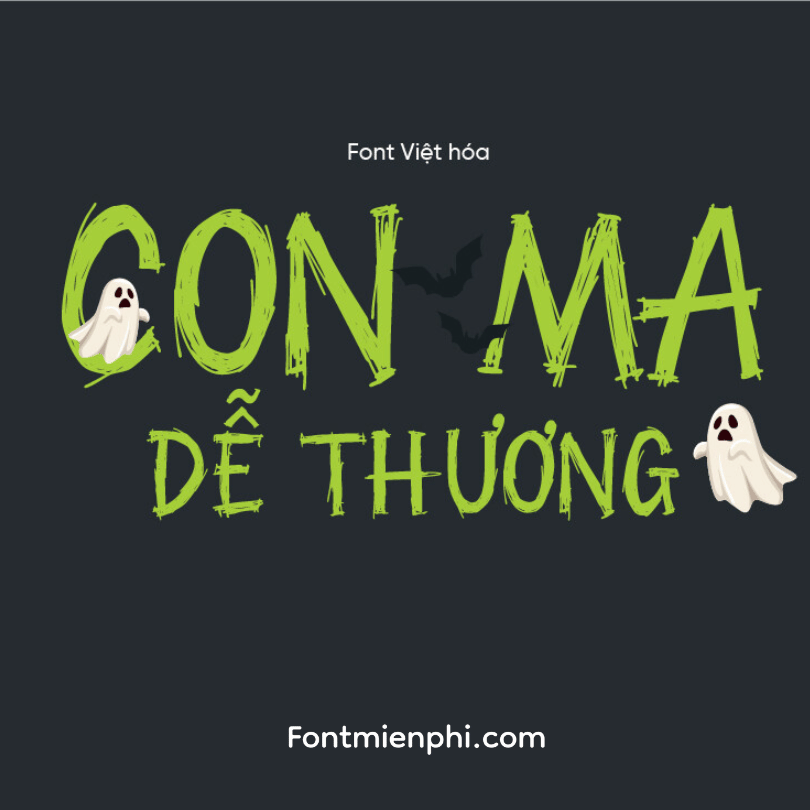
Font Việt hóa 1FTV VIP Rhope ,font Halloween
Font Việt hóa 1FTV VIP Rhope ,font Halloween – Phông Chữ Halloween Kinh Dị Đẳng Cấp
1FTV VIP Rhope là font chữ Việt hóa cao cấp với phong cách Halloween đậm chất kinh dị và huyền bí. Với những nét chữ sắc nhọn kết hợp hiệu ứng rách nát, font chữ này sẽ mang đến cho thiết kế của bạn vẻ ngoài ma mị và ấn tượng.
ĐẶC ĐIỂM NỔI BẬT:
✔ Phong cách kinh dị đậm chất Halloween – nét chữ đứt gãy, hiệu ứng máu me và rách nát
ỨNG DỤNG HOÀN HẢO:
• Thiết kế poster phim kinh dị, Halloween
• Bìa sách/truyện ma, tạo hình nhân vật quỷ dị
• Thiệp mời tiệc Halloween đáng sợ
• Thiết kế áo thun, vật phẩm Halloween